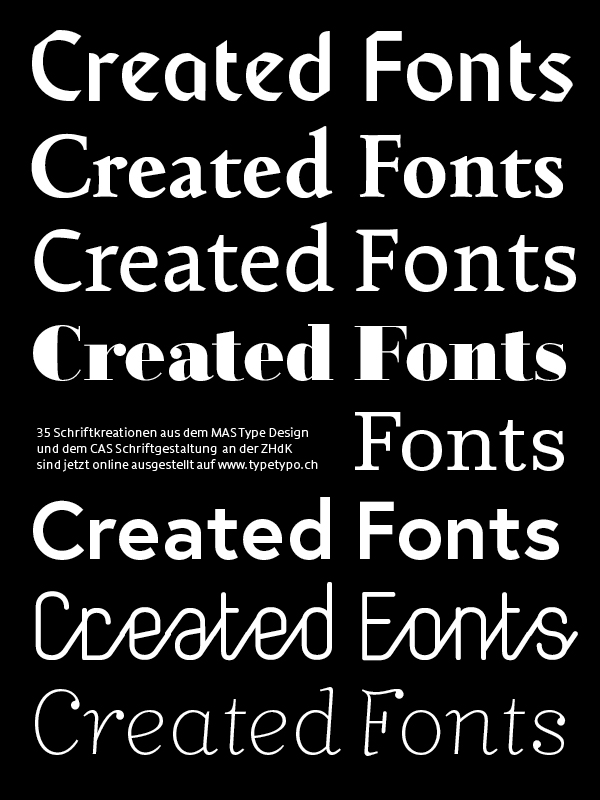
In den Nachdiplomstudiengänge «CAS Schriftgestaltung» und «MAS Type Design» an der Zürcher Hochschule der Künste (ZHdK) werden seit mehreren Jahren Textschriften mit höchstem Anspruch an Lesbarkeit, Ästhetik, technischem Standard und für solide Anwendbarkeit entwickelt. Den Schriftentwürfen liegt jeweils ein von den Studierenden definiertes Konzept zu Grunde. Immer sind es visuelle Neuheiten, zum Teil auch Interpretationen und Variationen historischer Vorlagen, gelungene Versuche mittels Mischungen von Schrift- und Stilarten oder auch technisch problemlösungsorientierte Kreationen.
Einige Schriften, die dort entstanden sind, wurden von bekannten Schriftvertriebsfirmen wie zum Beispiel Linotype, FontShop und URW++ in ihr Programm mitaufgenommen. Nicht wenige wurden in diversen Fachpublikationen vorgestellt oder einzelne mit international renommierten Auszeichnungen honoriert.
Auf der Website typetypo.ch wird nun zum ersten Mal eine breite Auswahl dieser Schriften online präsentiert. Diese Übersicht soll einerseits die Vielfalt wie auch die Qualität der in den letzten Jahren entstandenen Schriften aufzeigen, und dem Besucher einen Blick auf die Merkmale wie auch die Charakterisitk der Schriften ermöglichen.